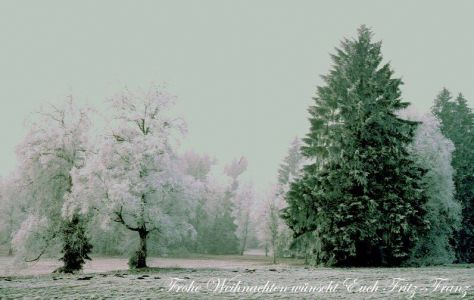
Schrift für Weihnachtskarte gesucht?
Ganz neutrale Neugier:
Warum empfiehlst Du diese Schrift als passend für Weihnachtskarten?
Weil der Schriftname "Xmas" enthält?
Oder wegen der in die Darstellung der Lettern eingestreuten Punkte, die vermutlich Schneeflocken symbolisieren wollen?
Oder aus welchem anderen Grund ist das eine geeignete Schrift für Weihnachtskarten?
Im Gegenzug – was ist eigentlich eine Weihnachtsschrift?
Irgendein "festlicher" Scriptfont, Didot Italic oder was? Wie man sieht, habe ich (auch hier) Schwierigkeiten mit Weihnachten.
Genau aus diesem Grunde fragte ich, was an dieser Xmas-Schrift weihnachtlich sein soll (egal, ob nun im ursprünglichen Sinne oder im konsum-orientierten).
Gute Frage, die ich mir auch gestellt habe. Ausgehend von der Fragestellung "Schrift für Weihnachtskarte gesucht" hätte man natürlich alle Schriften aufzählen können, weil die Formulierung es offen lässt, oben eine Schrift mit weihnachtlichem Flair oder Irgendeine gesucht wird. Ich habe für mich den Schluss gezogen, dass er/sie einen Font mit weihnachtlichem Flair meint. Stellt sich natürlich die Frage, was ein weihnachtlicher Font ist. Ein Font, der aus Lebkuchen zusammengebastelt ist? Ein Font mit harten, eckigen Serifen der ausschaut wie ein Weihnachtsbaum oder rund wie Christbaumkugeln ist? Ich weiß es nicht. Darum bleibt mir nur der Anhaltspunkt, welchen der Zeichner des Fonts mir gibt. Und in diesem Fall ist es ein Weihnachtsfont und als dieser wird er auch beschrieben. Hätte der Gestalter geschrieben, er hätte den Font speziell für Gurken entworfen, könnte ich mich dem auch nicht wiedersetzen. Ergo der Font ist für mich deshalb weihnachtlich, weil der Zeichner ihn für diesen Zweck entwickelt hat.
Damit Allesgute auch mal einen anderen Vorschlag bekommt: wie wäre es denn mit der Zapfino?
Verspielt-elegant, das ist doch so die richtige Richtung, oder suchst etwas ganz anderes?